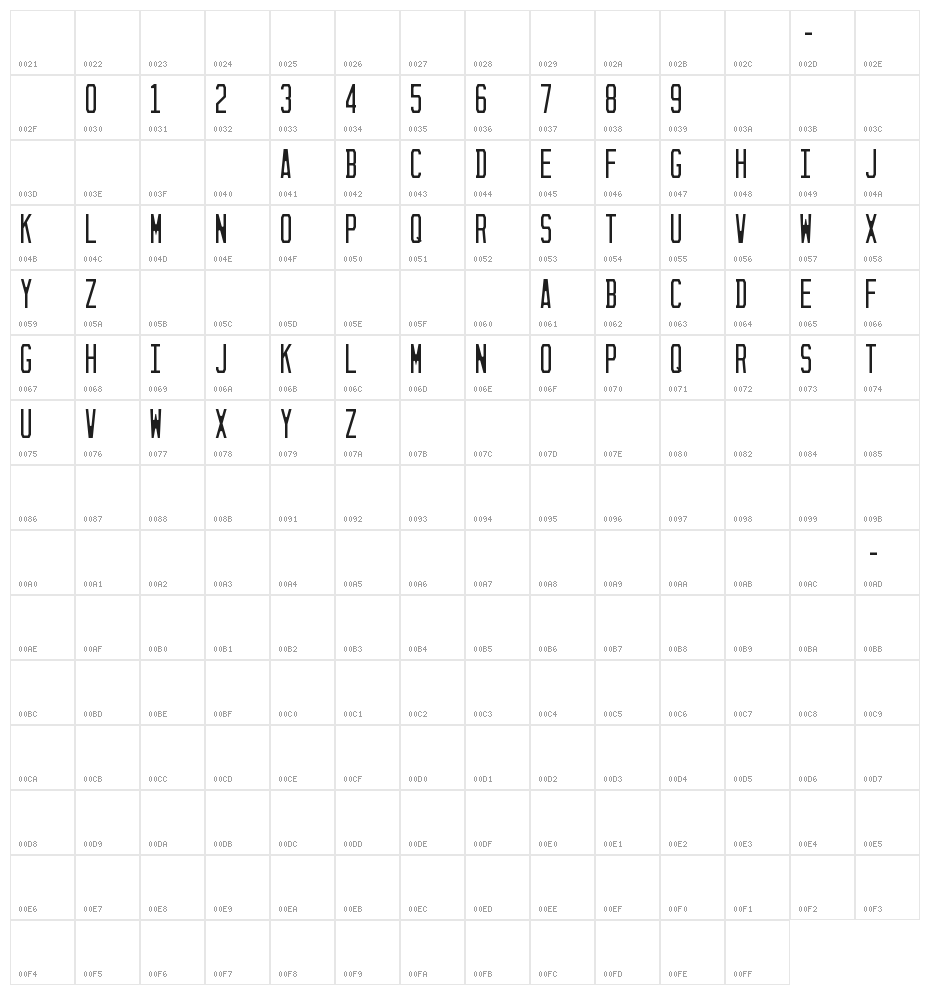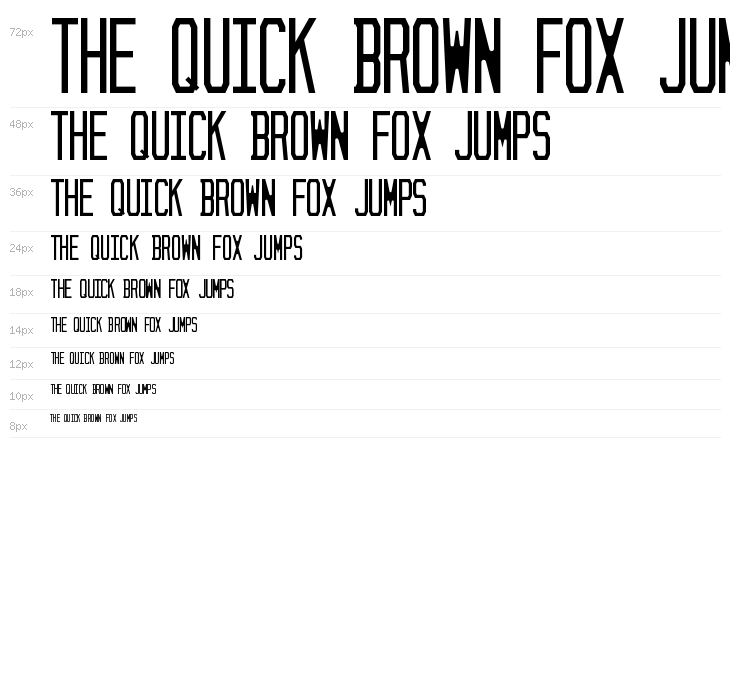
Sunshine State Font
| おすすめプロジェクト | This font is perfect for branding projects, posters, and any design requiring a strong, modern typeface. It can be used effectively in digital and print media where impactful text is needed. |